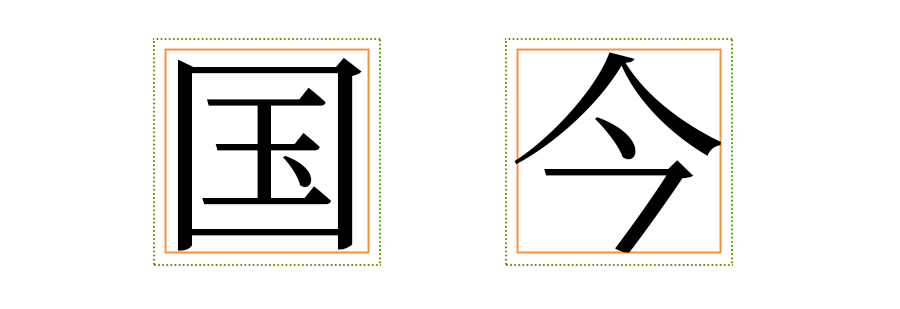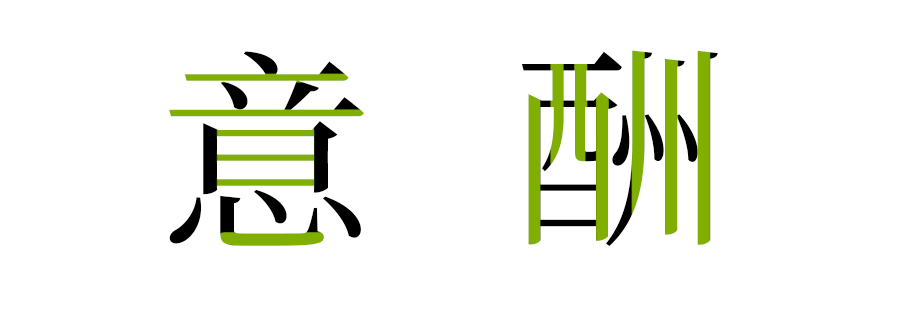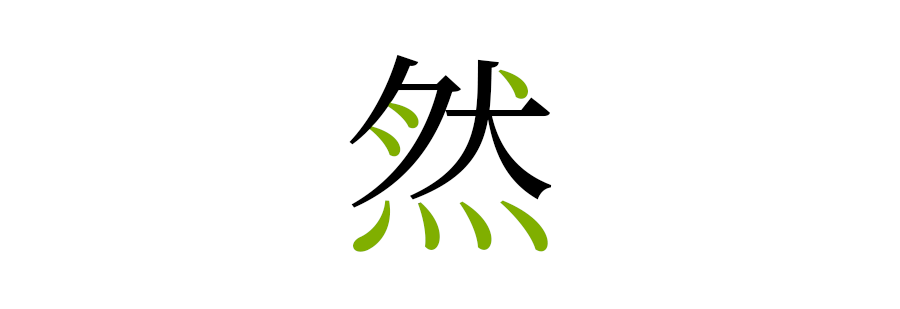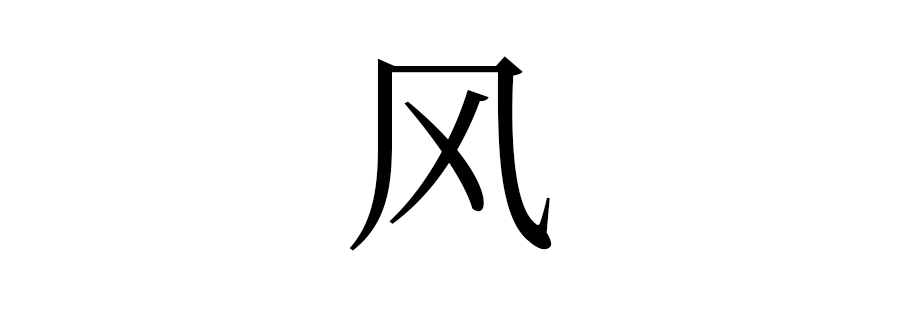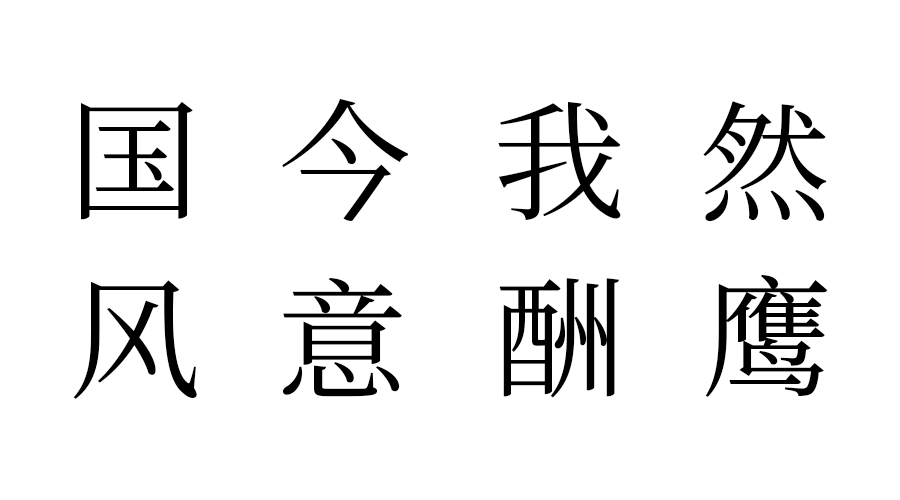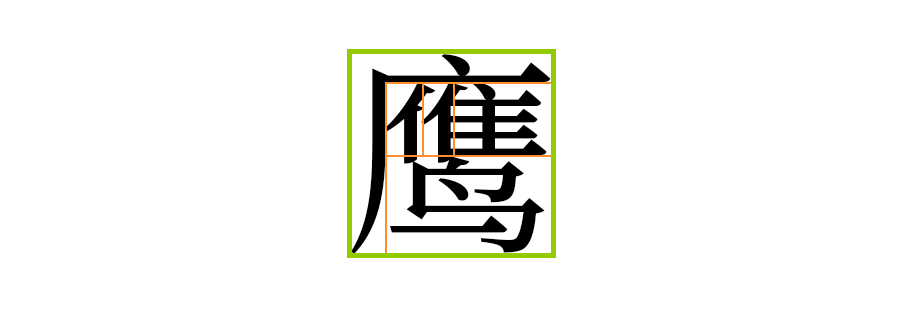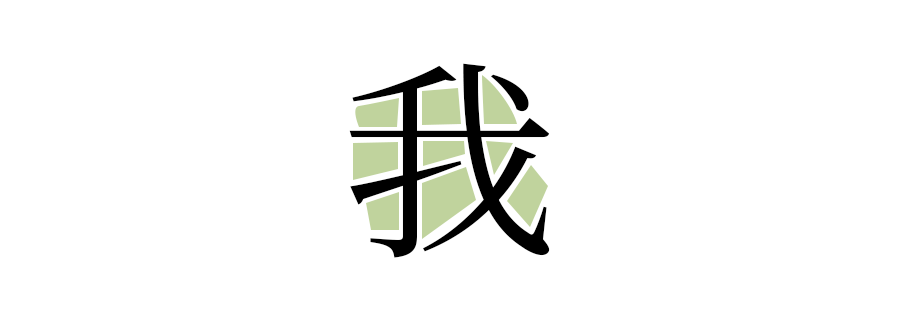
新手进行字体设计时,往往会疑惑从哪个字开始。下面介绍一些在字体设计中具有参考性的汉字,优先设计这些汉字可以帮助确定字体的基本特征和空间布局。
设计一套字,首先要确定字体的字面范围,“国”字呈方形,有助于确定字体的整体框架。“今”字呈菱形,有助于确定字体的字面范围。
“我”字的笔画较为繁琐,字体的空间划分较为完整,通过“我”字可以推敲字体内部空间的划分。
“然”字包含多种点笔画,可以作为点笔画设计的参考。
“风”字包含较难处理的笔画和复杂的结构,有助于练习处理复杂笔画。
“意”字和“酬”字横竖笔画特别多,合适的处理可以为后续类似情况提供参考。
“鹰”字结构较为复杂,包含上下、左右、包围等各种嵌套结构,有助于全面测试字体设计的各个方面。
通过这些字的练习,新手可以逐步掌握字体设计的基本技巧和要点。